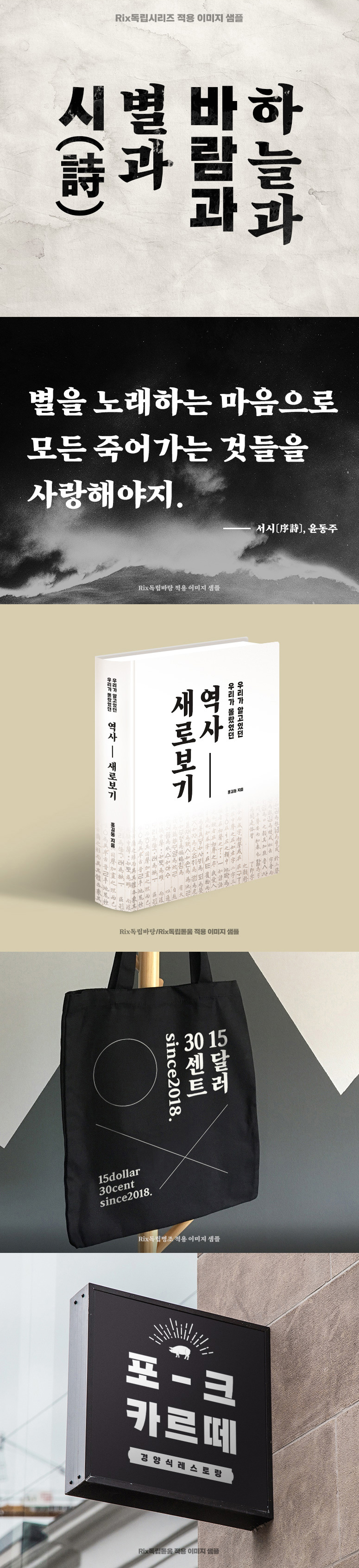
Rix독립시리즈 - 독립고딕 / 독립돋움 / 독립명조 / 독립바탕
독립 개화의 시대적인 배경과 그 분위기를 담아 제작되었으며 꽉 찬 형태의 두꺼운 웨이트와 모듈을 지니고 있습니다. 모던한 인상을 주고 복고적인 느낌을 표현하였습니다. 독립시리즈는 세로쓰기로 사용될 때를 고려하여 한글 한 벌을 추가하였으며 문장 부호 및 다양한 환경을 고려하여 세심하게 디자인되었습니다.